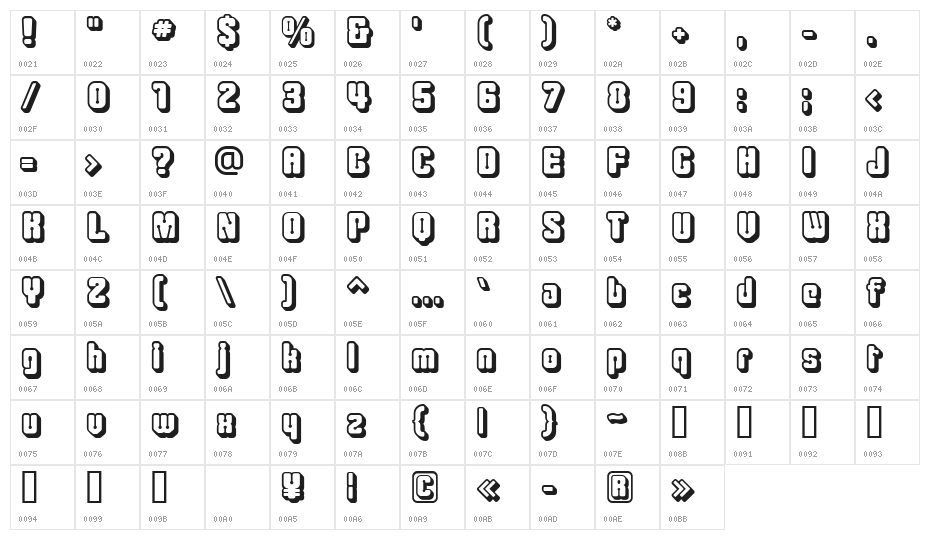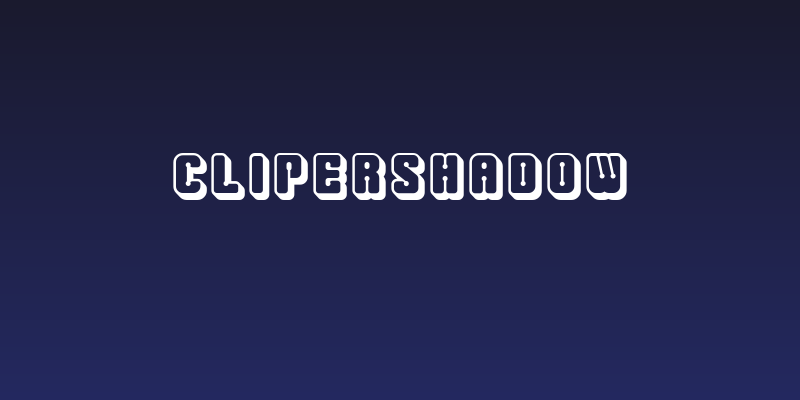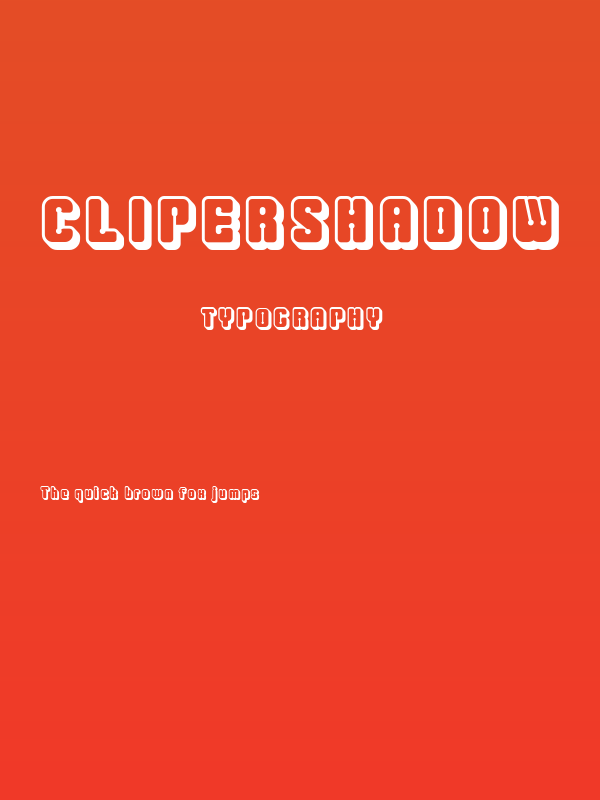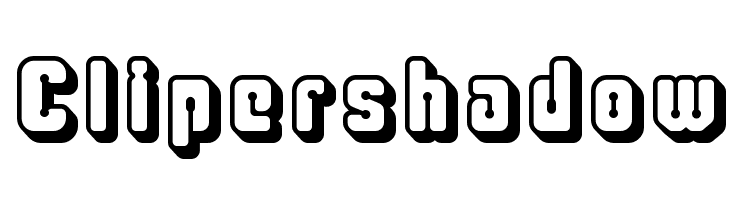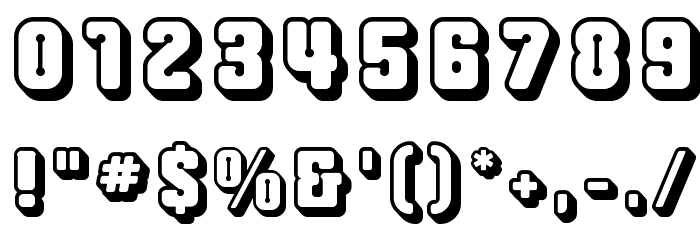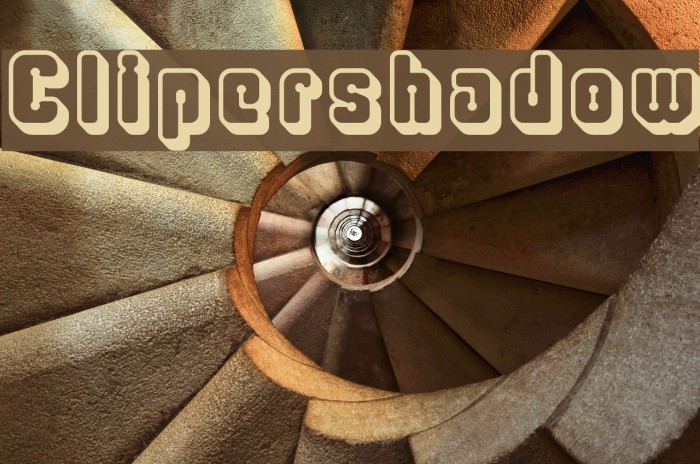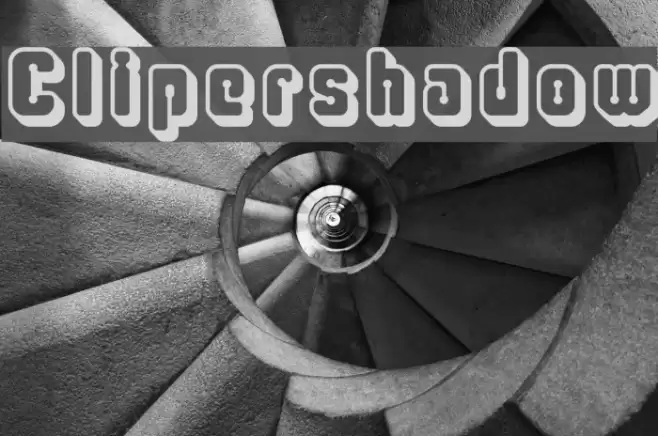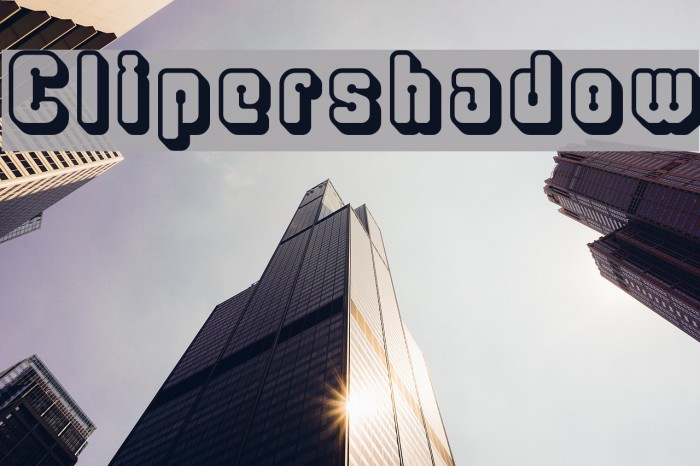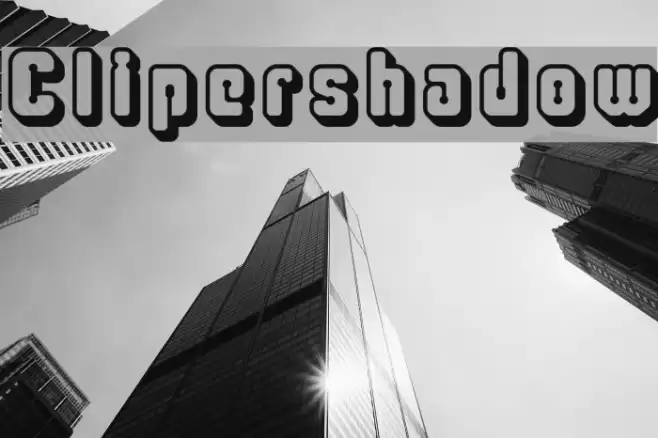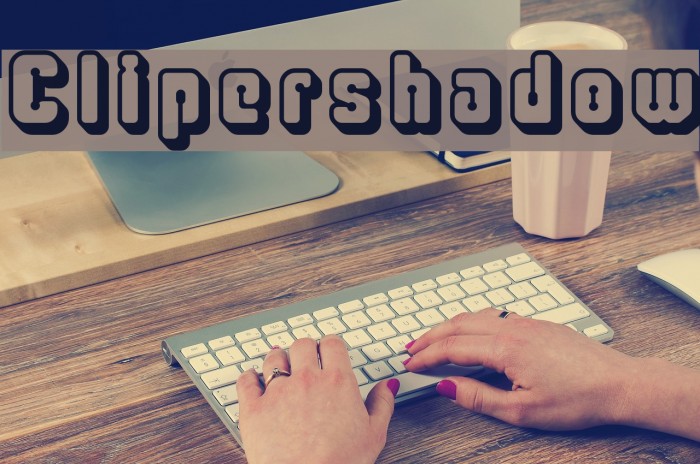
Clipershadow Font
| Stil general | Playful, Retro |
| Proiecte propuse | Ideal for use in comic books, retro-themed posters, children's books, and playful branding projects. |